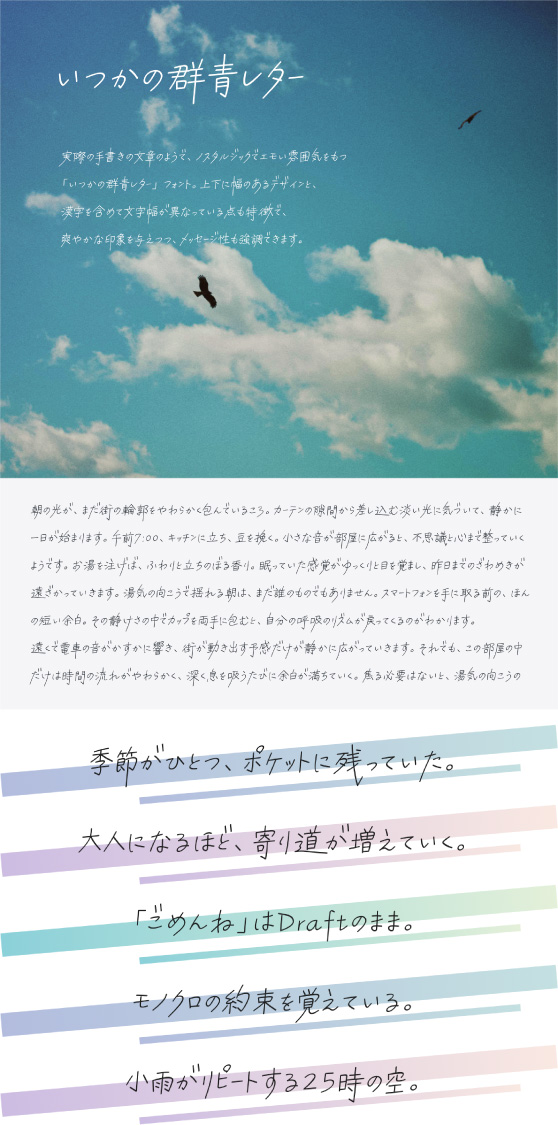
リアル手書き
いつかの群青レター Kw-N
Itsuka-no-Gunjo-Letter-Kw-N
ノスタルジックでエモい雰囲気を持つフォントです。メッセージ性を強調したい場面にもおすすめです。コトノハワークスの手書き風フォント第1弾です。
通常のフォントより上下に飛び出しているデザインのため、ご利用のアプリによっては見切れる場合があります。 漢字の幅も一定ではないため、一部アプリでは正常に動作しません。縦書きには対応しておりません。